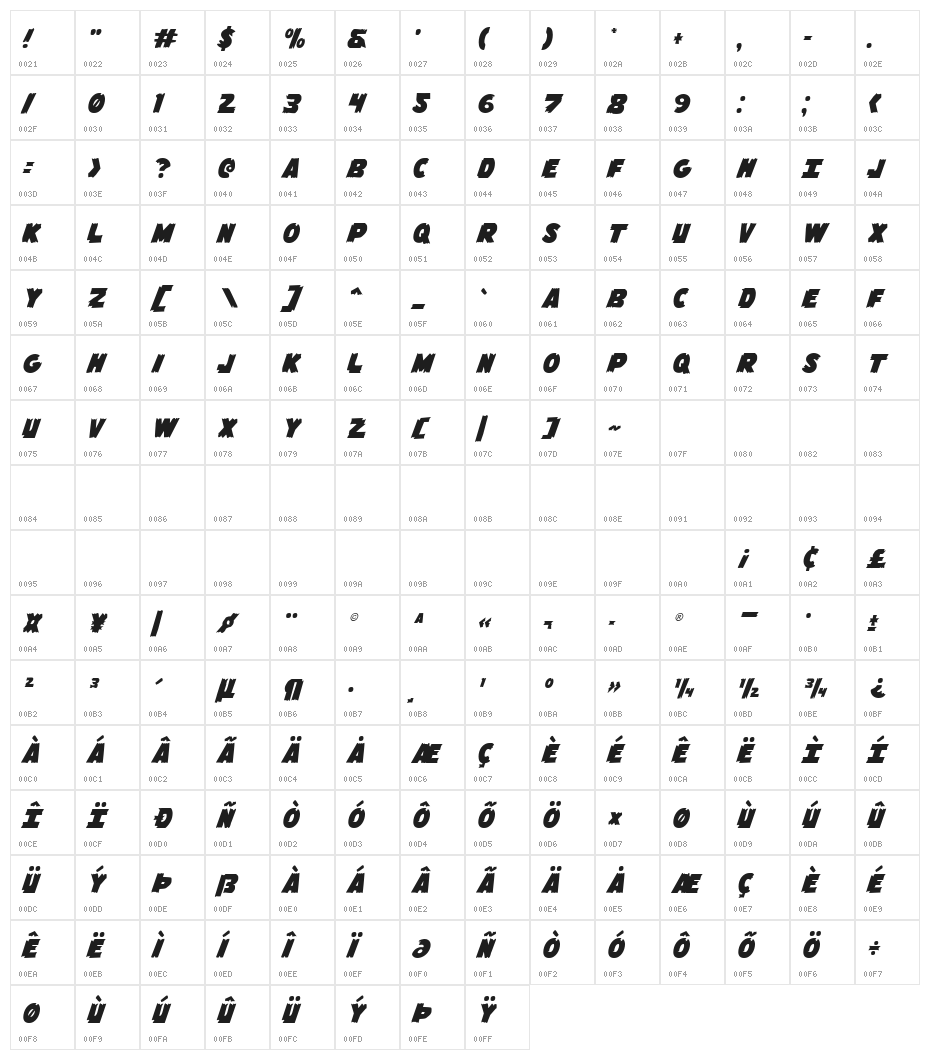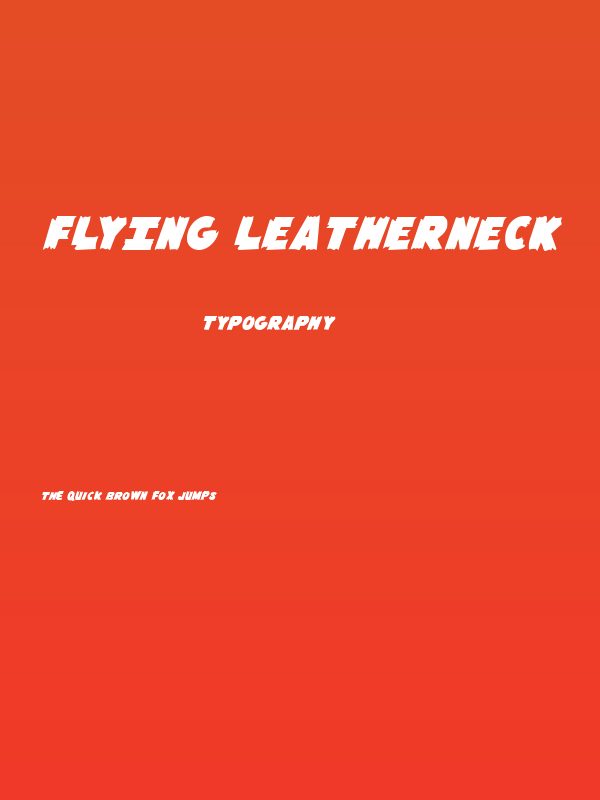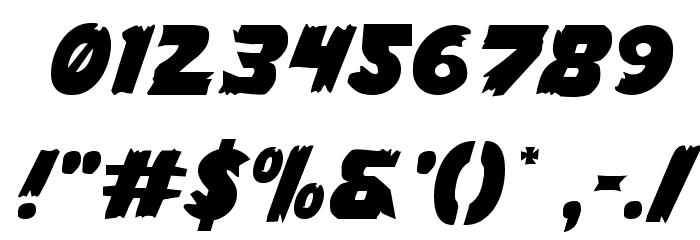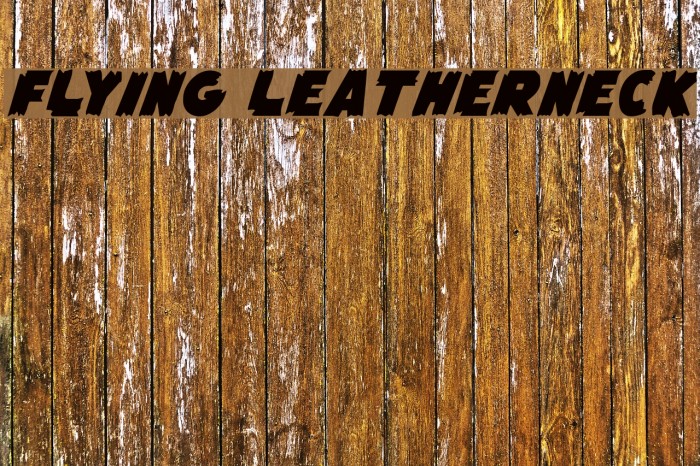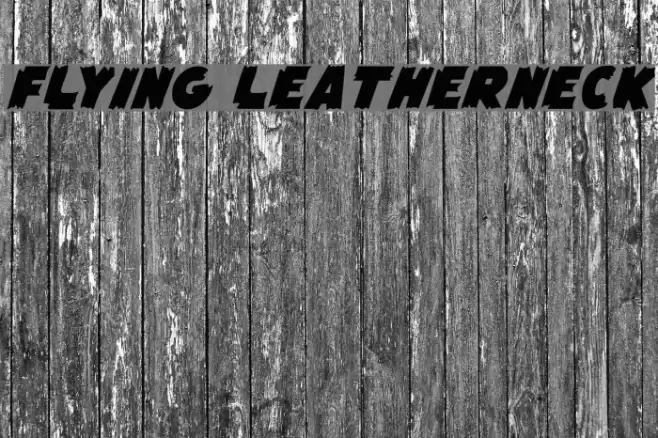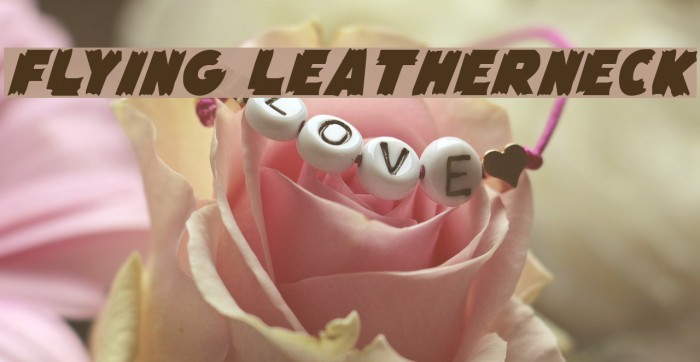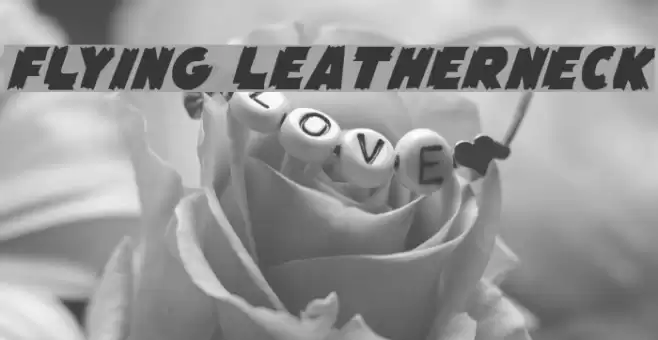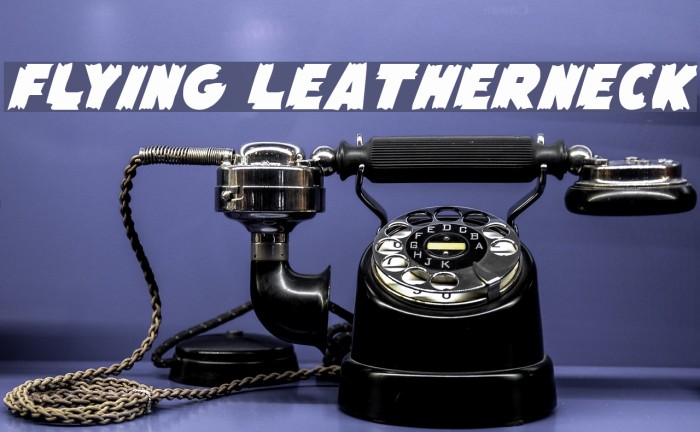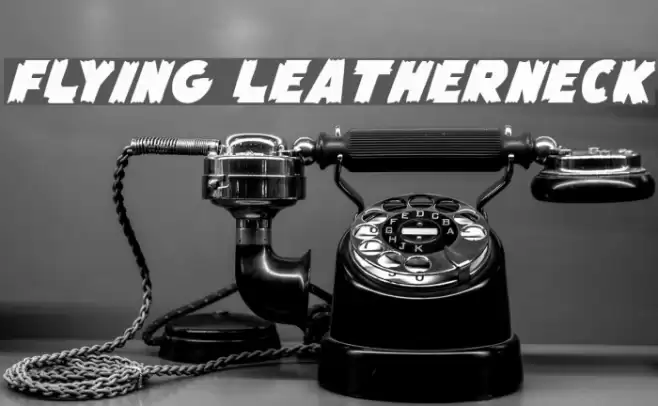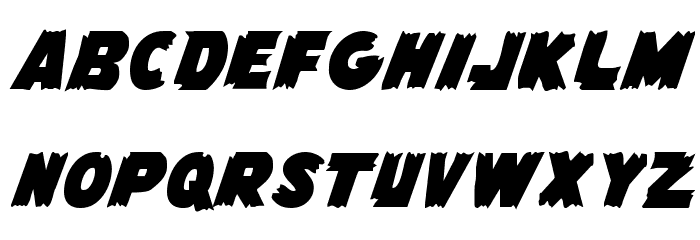
Flying Leatherneck Font
| Estilo geral | Modern, Decorative |
| Projetos propostos | Ideal for use in action-themed posters, video game titles, sports branding, and any project requiring a strong, impactful visual presence. |